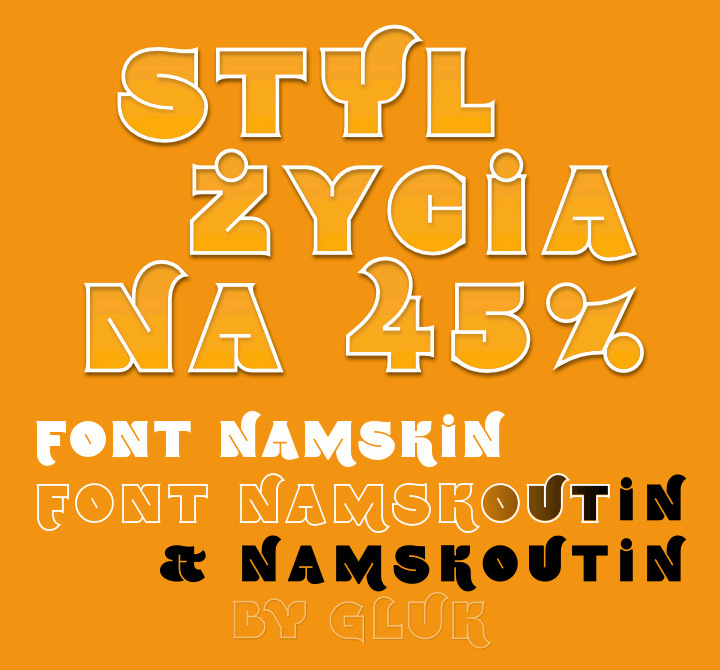
A Namskout é uma família de fontes display criada pelo designer Hamilton, que se destaca por seu estilo inovador e elegante. Esta fonte traz consigo um equilíbrio perfeito entre a simplicidade moderna e o charme gráfico clássico, tornando-a ideal para uso em materiais visuais criativos. Com linhas retas e formas geométricas, Namskout consegue capturar atenção de maneira forte. Suas letras são bem projetadas para serem usadas tanto nos títulos quanto nas seções principais de um documento ou website. O resultado é uma fonte que não apenas destaca o texto sobre a qual está centrada, mas também contribui significativamente para criar um design visual arrojado e moderno. Seja em aplicativos de design gráfico ou sites web, Namskout oferece aos criadores de conteúdo a oportunidade de incorporar estilos únicos que ressaltam o texto como se fosse uma obra-prima visual. A sua característica mais chamativa é certamente seu carácter capaz de transmitir um ar moderno e distinto, sem perder a elegância necessária para projetos profissionais e publicitários. O uso desta fonte em projetos digitais ou impressos pode transformar o texto num elemento de destaque e um design gráfico vibrante. Como parte da família Namskout, ela proporciona uma variedade de opções estilísticas que permitem adaptá-la ao seu próprio estilo criativo.